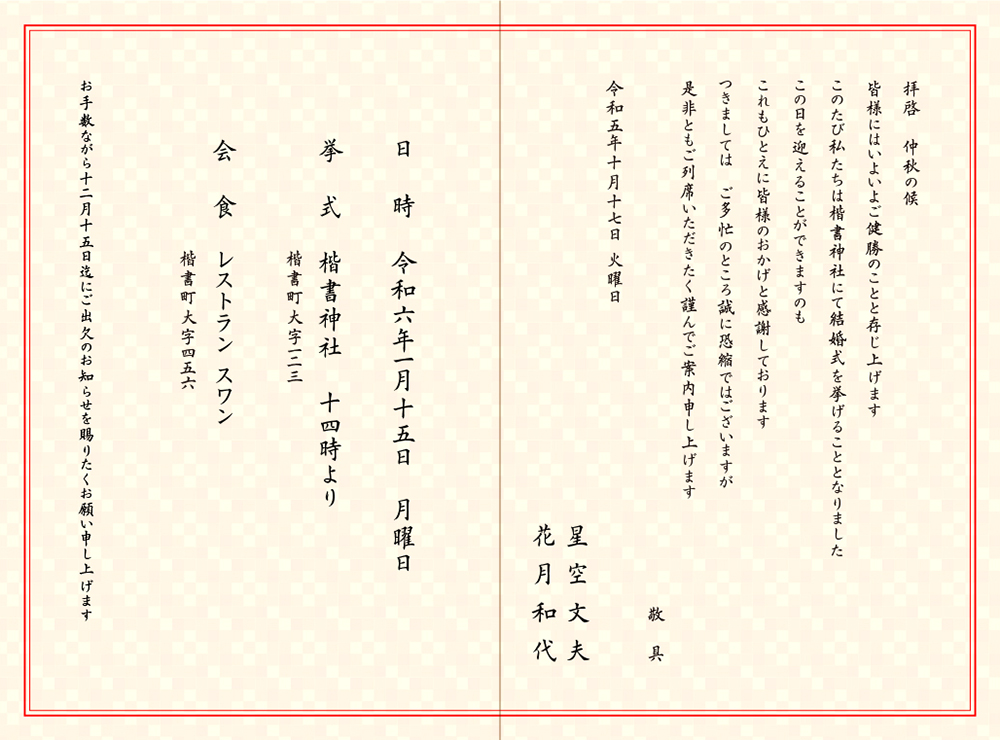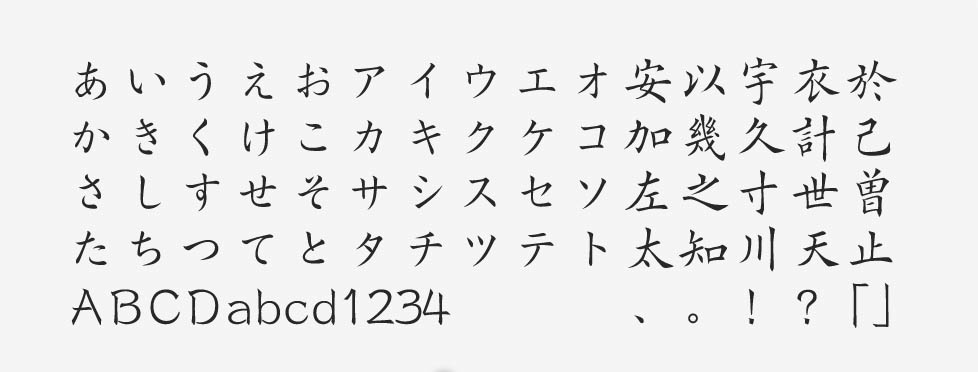
「欧体楷書」について
欧体楷書は、中国の唐の時代の書家であった欧陽詢(おうようじゅん)の書を参考にして開発されました。端正な文字が楷書体として現代に蘇っています。2006年には欧体楷書の漢字を生かした別かな作成のプロジェクトも開始され、翌年に「欧体楷書 藤かな」として完成しています。
「欧体楷書」の特徴
従来の活字由来の楷書体と比べると、欧体楷書には伸び伸びとした雰囲気があります。あえて大きさを揃えすぎず、文字それぞれの個性が消えないように配慮されたデザインです。颯爽とした印象で、品格や威厳も感じさせます。楷書体であるため、特に案内状や挨拶状などには使いやすいでしょう。
文字の本来の特徴を生かしたフォルムは、同時に文字ごとに異なる美しい余白も生み出します。文字列を組んだときに、情感豊かな抑揚が見えてくるフォントです。
楷書系の書体を使うような場面は限られますが、この欧体楷書はしっかりと覚えておくと良いでしょう。作例は神前式の案内状で、まさに欧体楷書の雰囲気が合致しやすい媒体です。どことなく優しい雰囲気もあり、とても良い感じに文字を組むことができました。